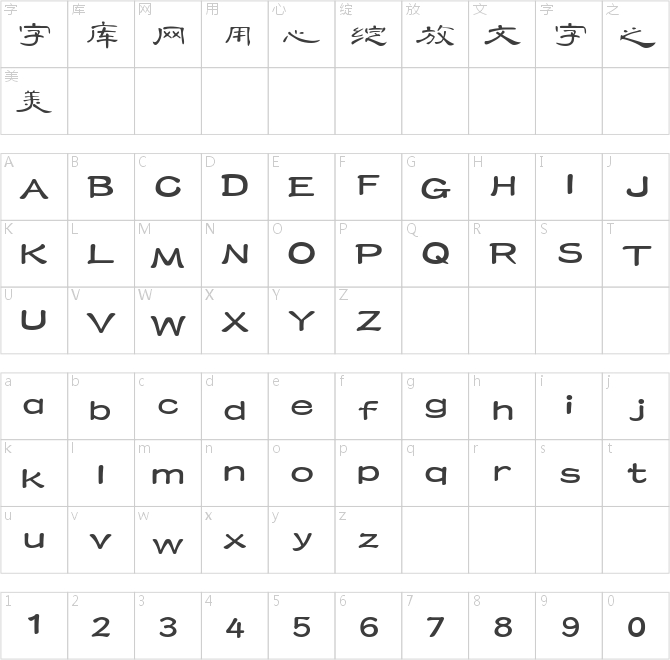
字体名称: 三极曹全碑简体
《曹全碑》属东汉末隶书完全成熟期的代表作品之一,它记载了东汉末年曹全镇压黄巾起义的事件,是研究东汉末年农民起义重要的历史资料,也是现存中国汉代石碑中保存比较完整、字体比较清晰的少数作品之一。其结字匀整,用笔方圆兼备,而以圆笔为主,风致翩翩,美妙多姿,是汉隶中秀美风格的代表。
三极曹全碑简体字体SJcaoquanbei字库是一款让人赏心悦目、百看不厌的中文字体,适合各类广告和产品包装设计应用,字体大小10.76MB,格式为ttf字体,上传用户是三极字库,作者/版权方为三极字库/蔡建文